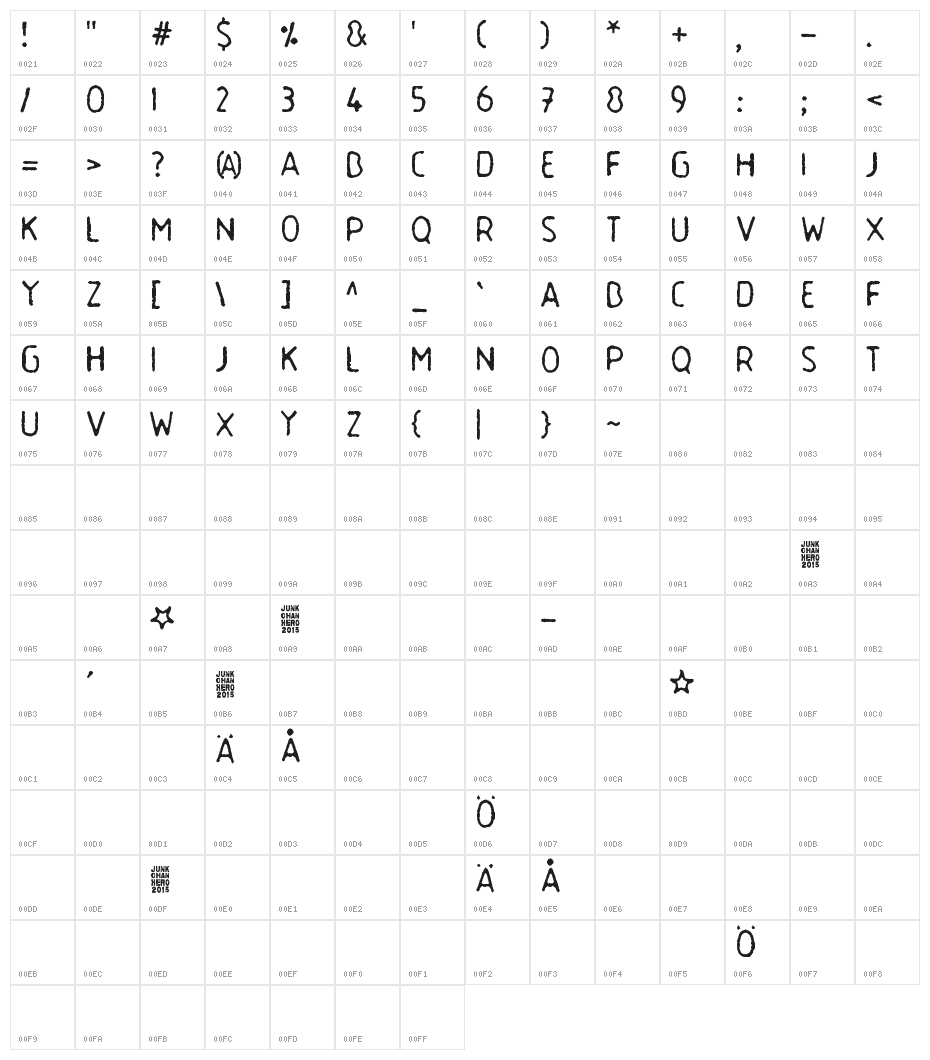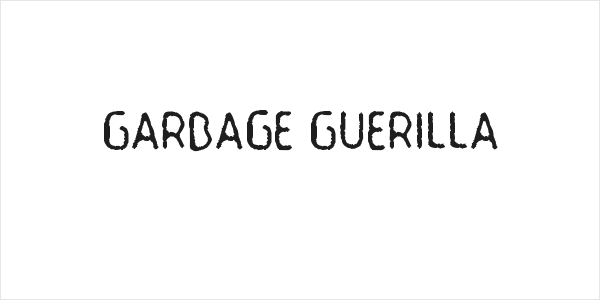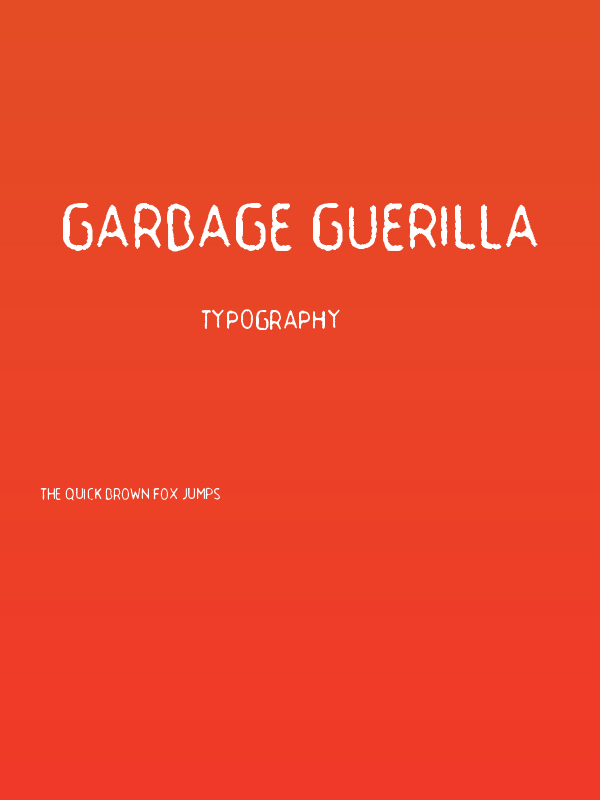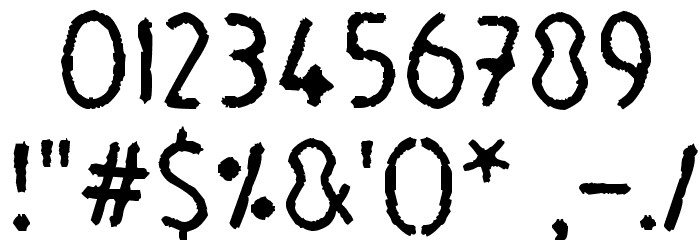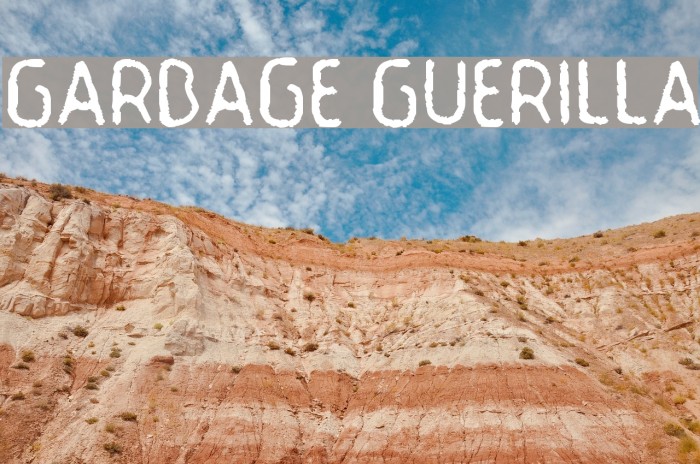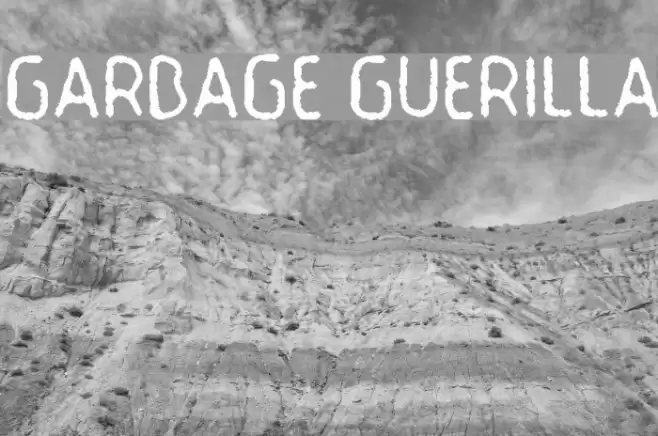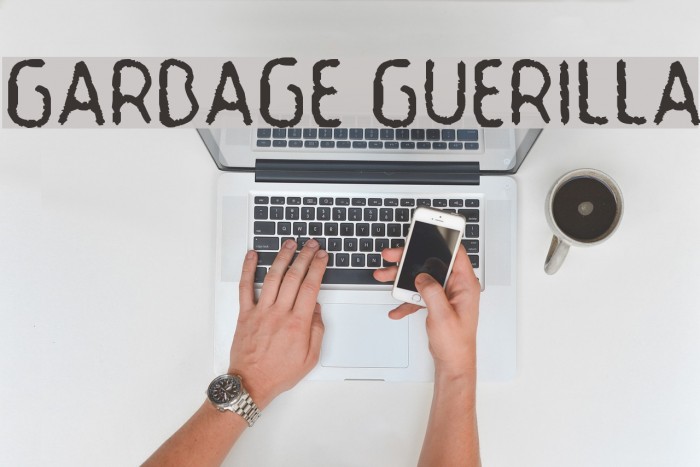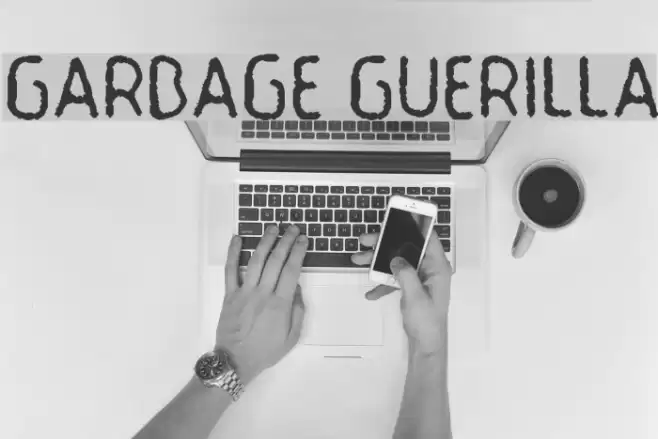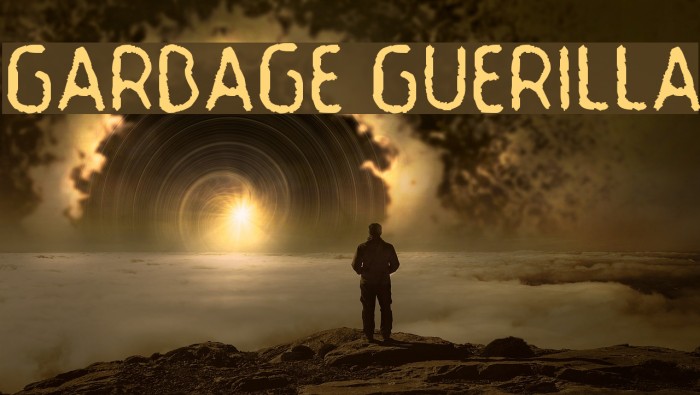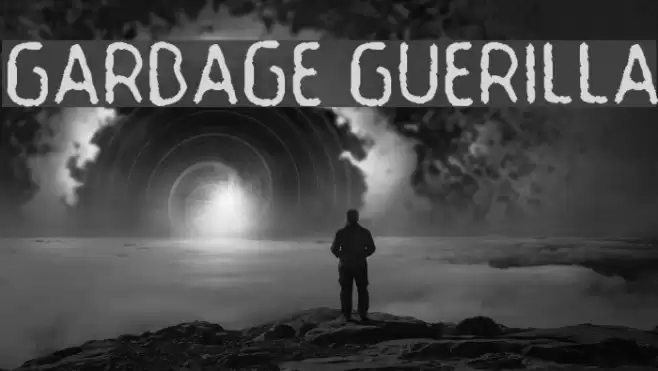
Garbage Guerilla Font
✎ Distorted Eroded
| Estilo general | Urban, Edgy, Distressed |
| Caso de uso | Headlines, Posters, Branding |
| Proyectos propuestos | Ideal for street art posters, album covers, edgy branding, and protest materials. |